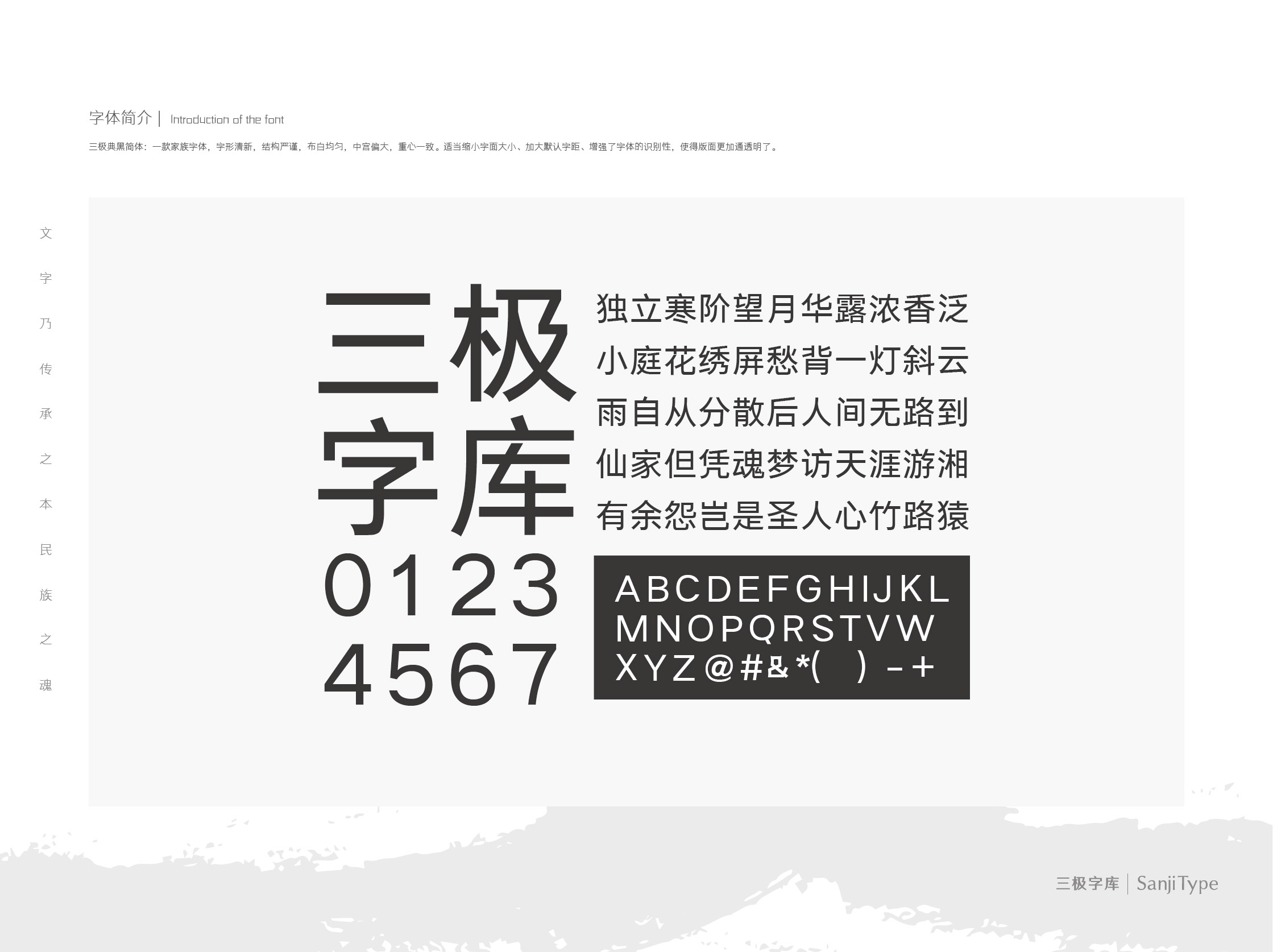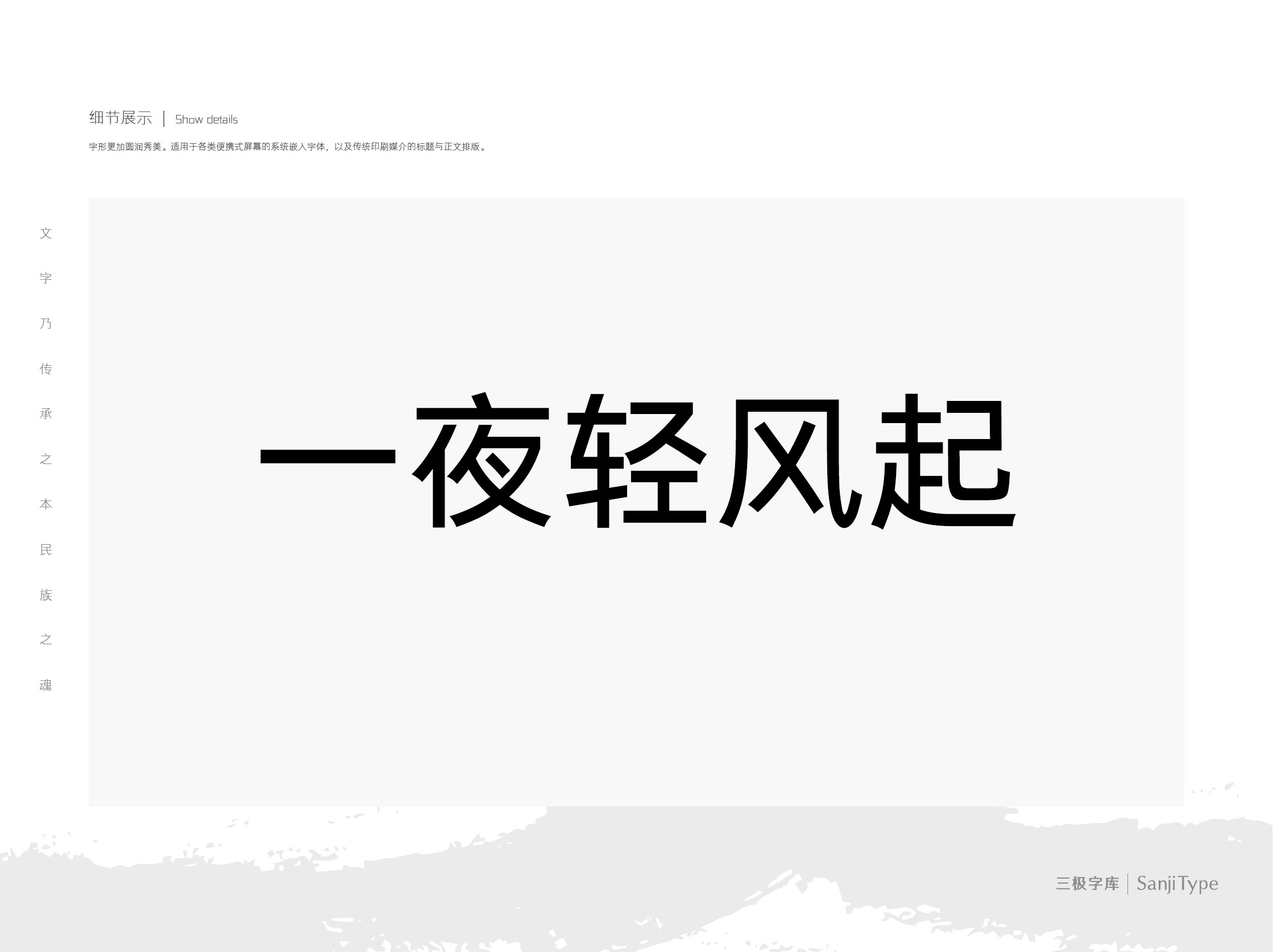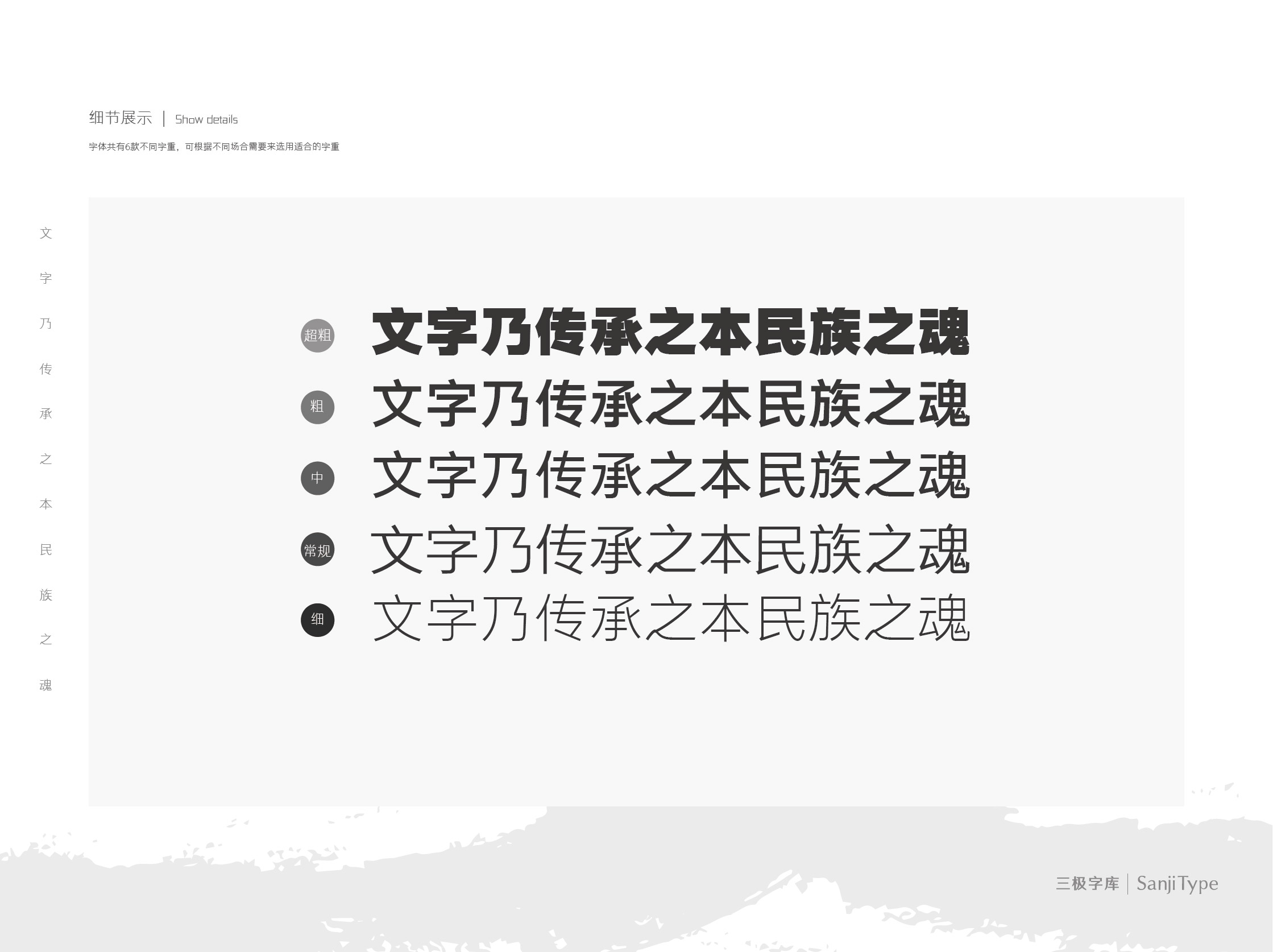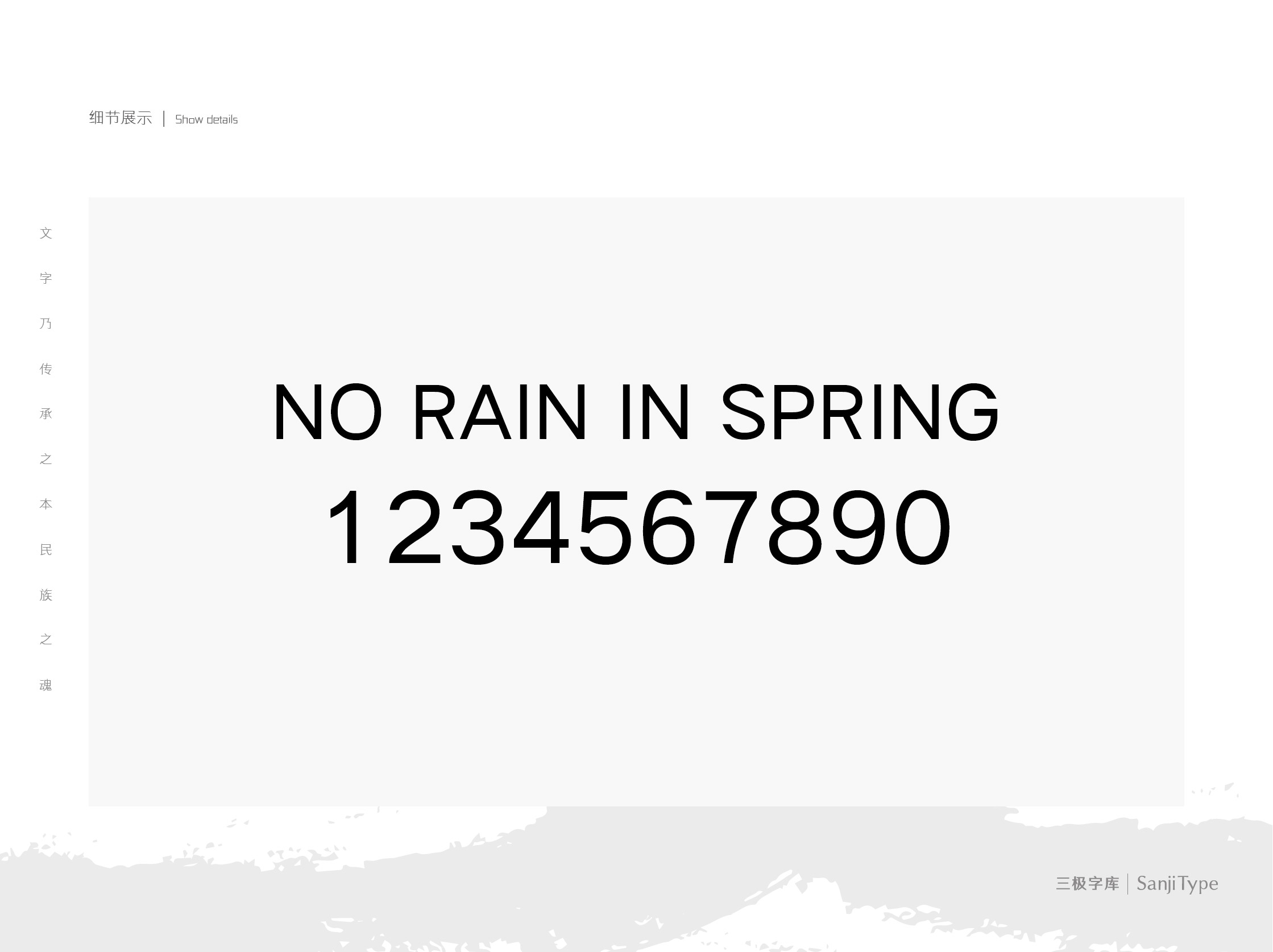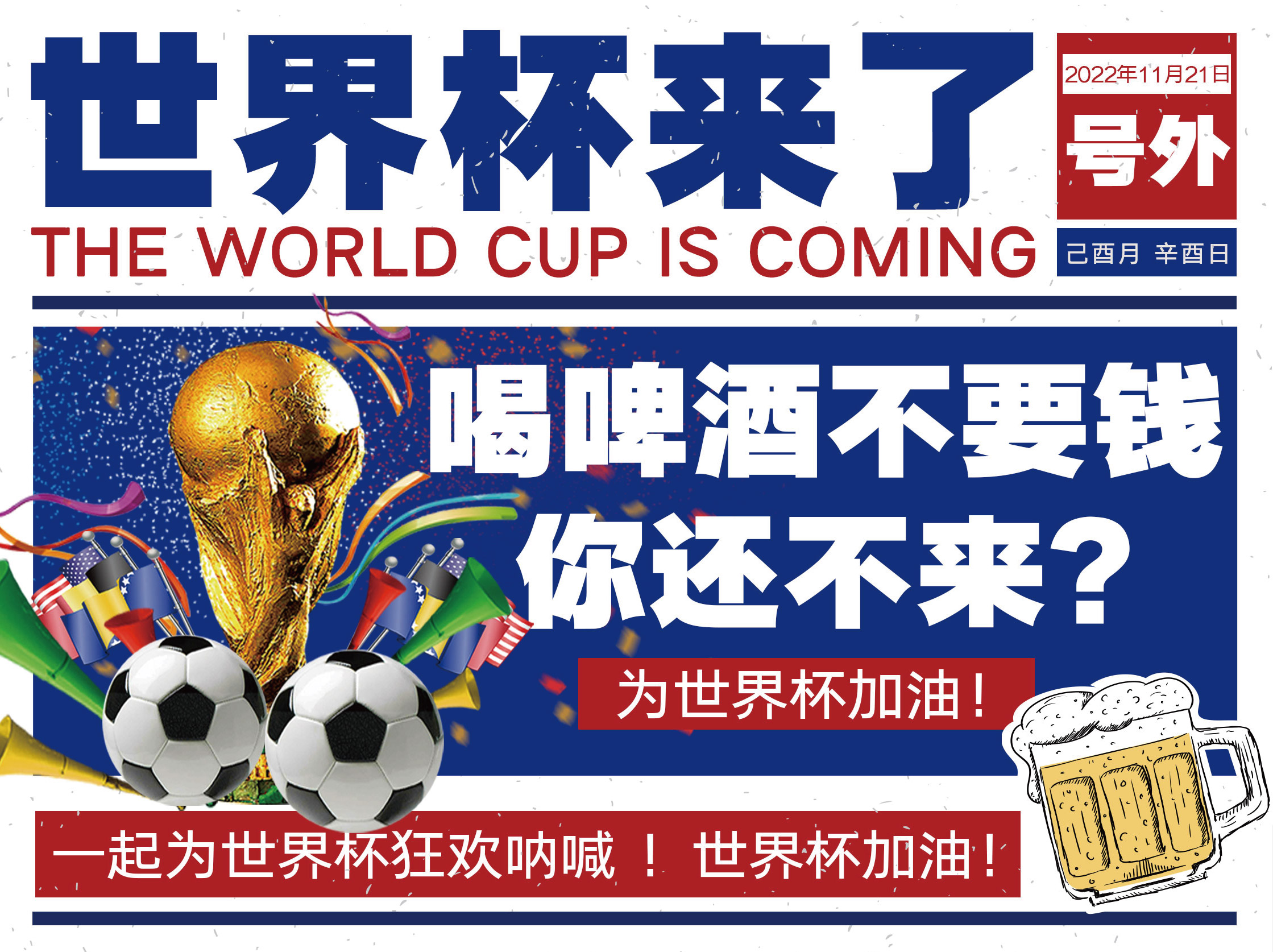
三极典黑简体是一款家族字体,字形清新,结构严谨,布白均匀,中宫偏大,重心一致。适当缩小字面大小、加大默认字距、增强了字体的识别性,使得版面更加通透明了。字形更加圆润秀美。适用于各类便携式屏幕的系统嵌入字体,以及传统印刷媒介的标题与正文排版。在品牌形象设计中作为logo设计辅助描述性文字视觉效果更佳。
适用媒介:报纸、杂志、书籍、广告、标志、宣传册、空间导视、包装、影视、屏幕显示、交互设计。